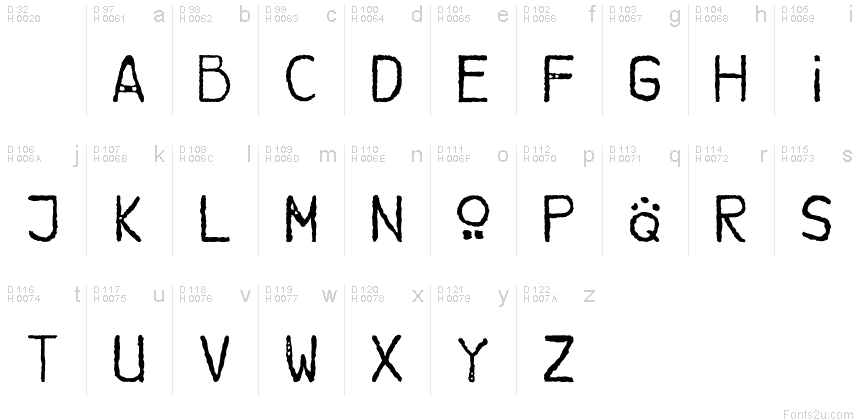
由 D.J.B. Henning 设计的 Brother Bear 是一款免费的侵蚀感显示字体,捕捉到了原始、手写划痕般的能量。字母呈现出斑驳与风化的质感,其不规则的轮廓如同木刻或粗糙纸张上的墨迹,为标题赋予了一种野性十足的叙事感,仿佛直接来自荒野。
使用 Brother Bear,能让你的标题瞬间充满冒险与不羁的气息。这款免费字体非常适合电影风格海报、奇幻书封、主题派对邀请函、游戏标题、YouTube 封面图以及角色标识设计。建议大号使用以获得最大视觉冲击力,并在小字部分搭配简洁的无衬线字体,以确保这些粗犷的字形既保持极高的可读性,又极具视觉感染力。